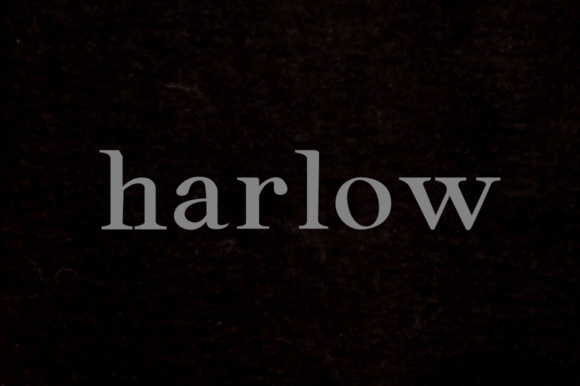
Harlow
Trouver les bons éléments de conception peut être un défi, mais Harlow propose une collection exceptionnelle qui rehausse instantanément votre travail.
Que vous créiez des produits POD (impression à la demande), des invitations de mariage ou des visuels pour les réseaux sociaux, Harlow est un choix idéal.